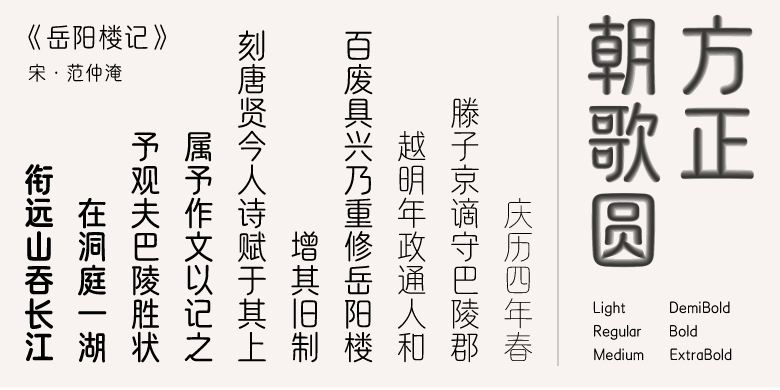
方正朝歌圆家族
字体品牌: 方正字库 设计师: 李月美 字体分类: 创意字体 字体属性: 精品字 字符集: 大陆简体(GB2312-80) 发布时间: 2022
灵感来源于古文字(从殷商甲骨文到秦篆),因此以商代都城“朝歌”命名,取高歌黎明,喜迎朝阳的美好意境。字形结合篆书圆体,具有古风韵味的同时又适当削弱了古文字严肃的历史感,能和一些轻古风的更现代的视觉元素搭配。